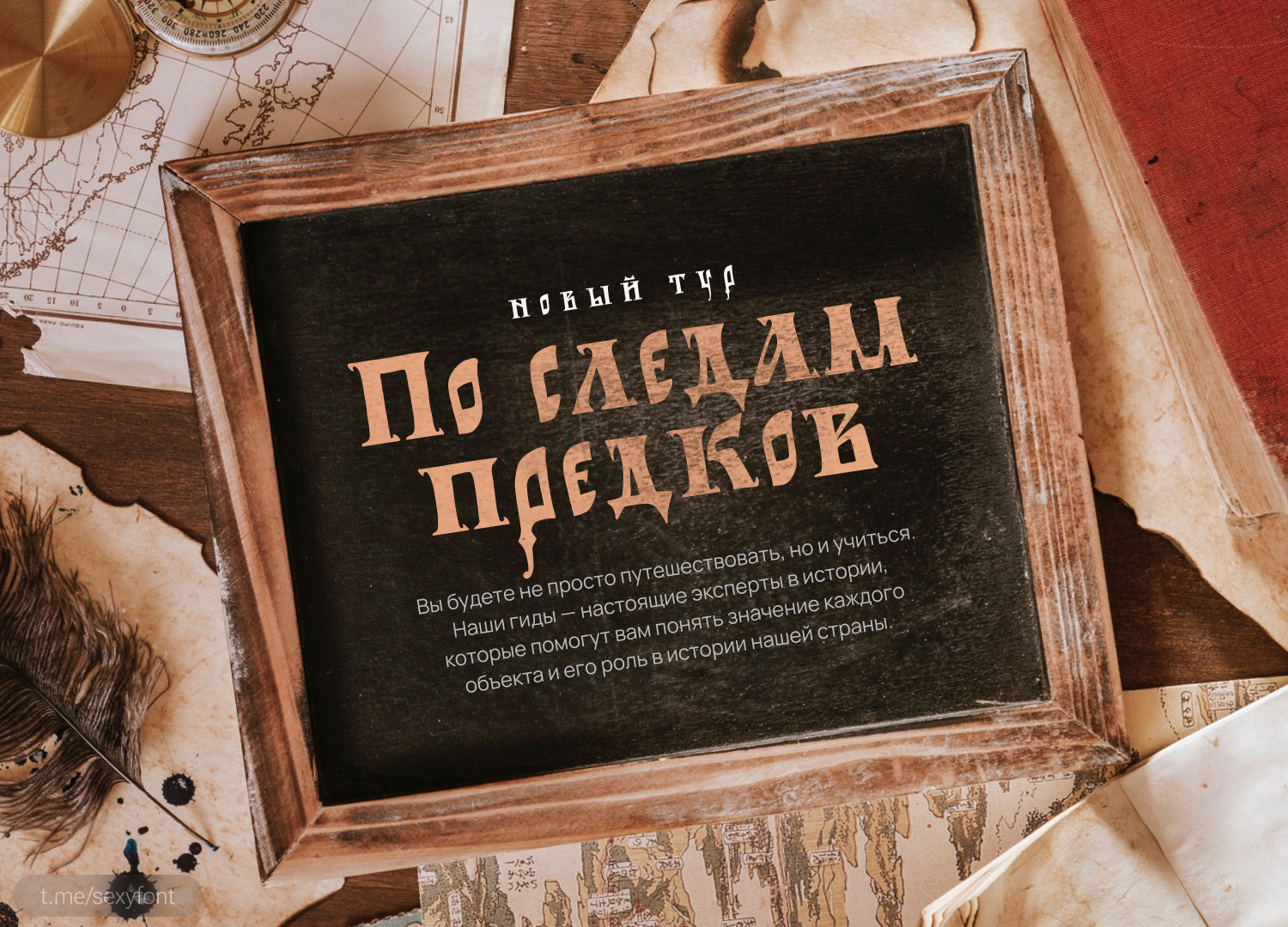
Шрифт «Добрый устав»
Шрифт «Добрый устав» — бесплатный кириллический шрифт, разработанный Дмитрием Тектовым . Он выполнен в старинном стиле, основанном на уставном письме.Автор: Дмитрий Тектов. Бесплатно для любых целей